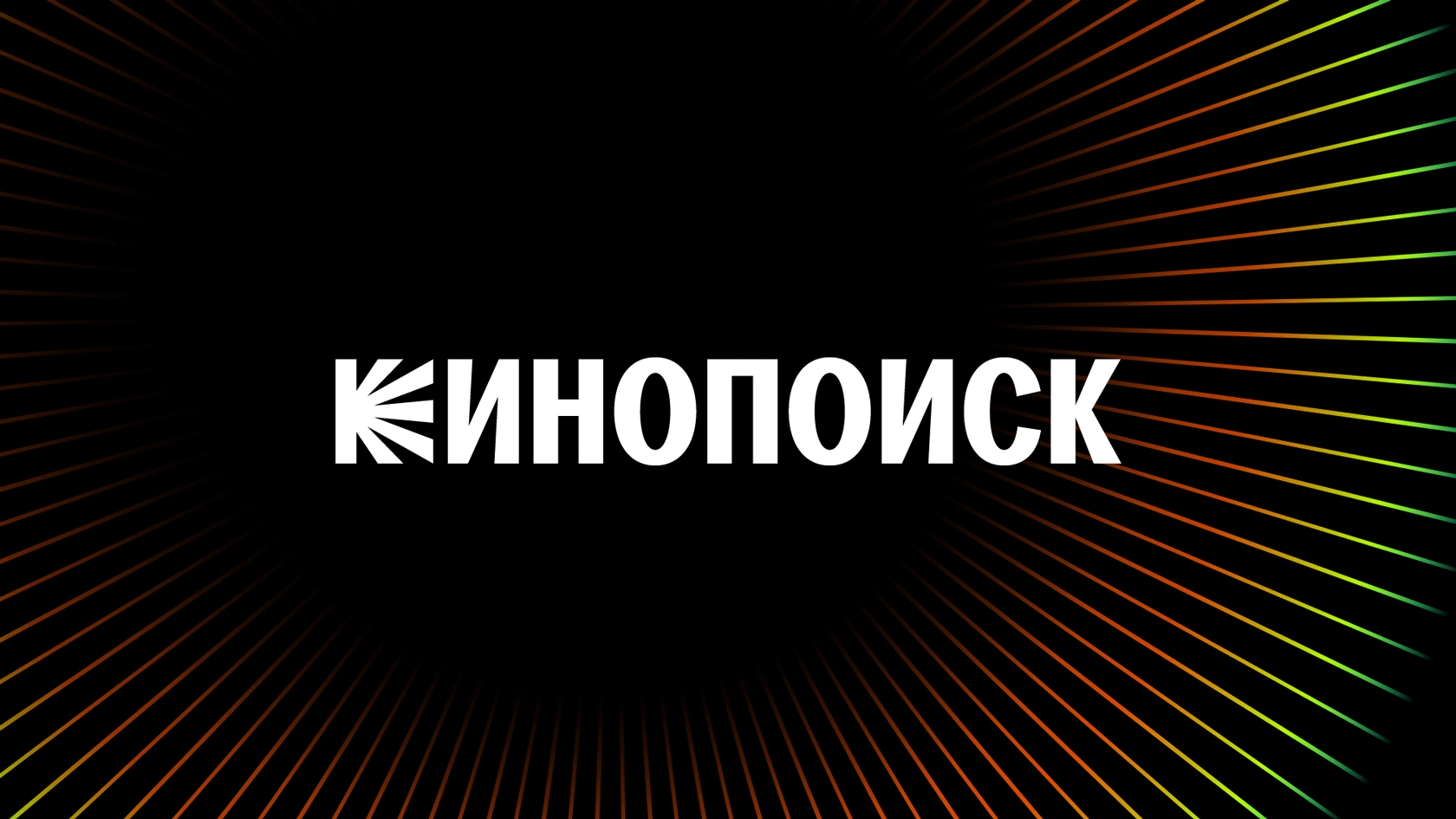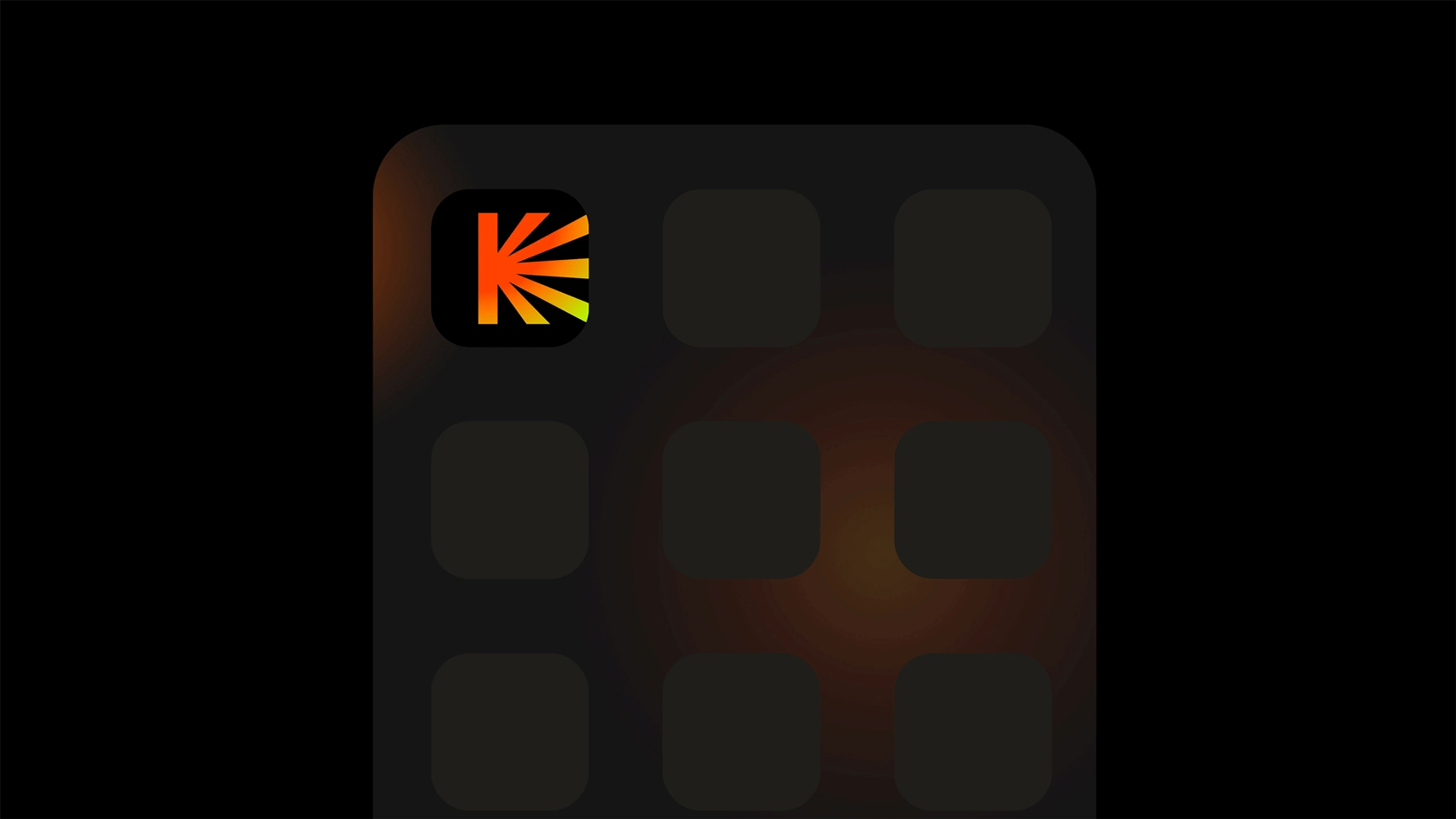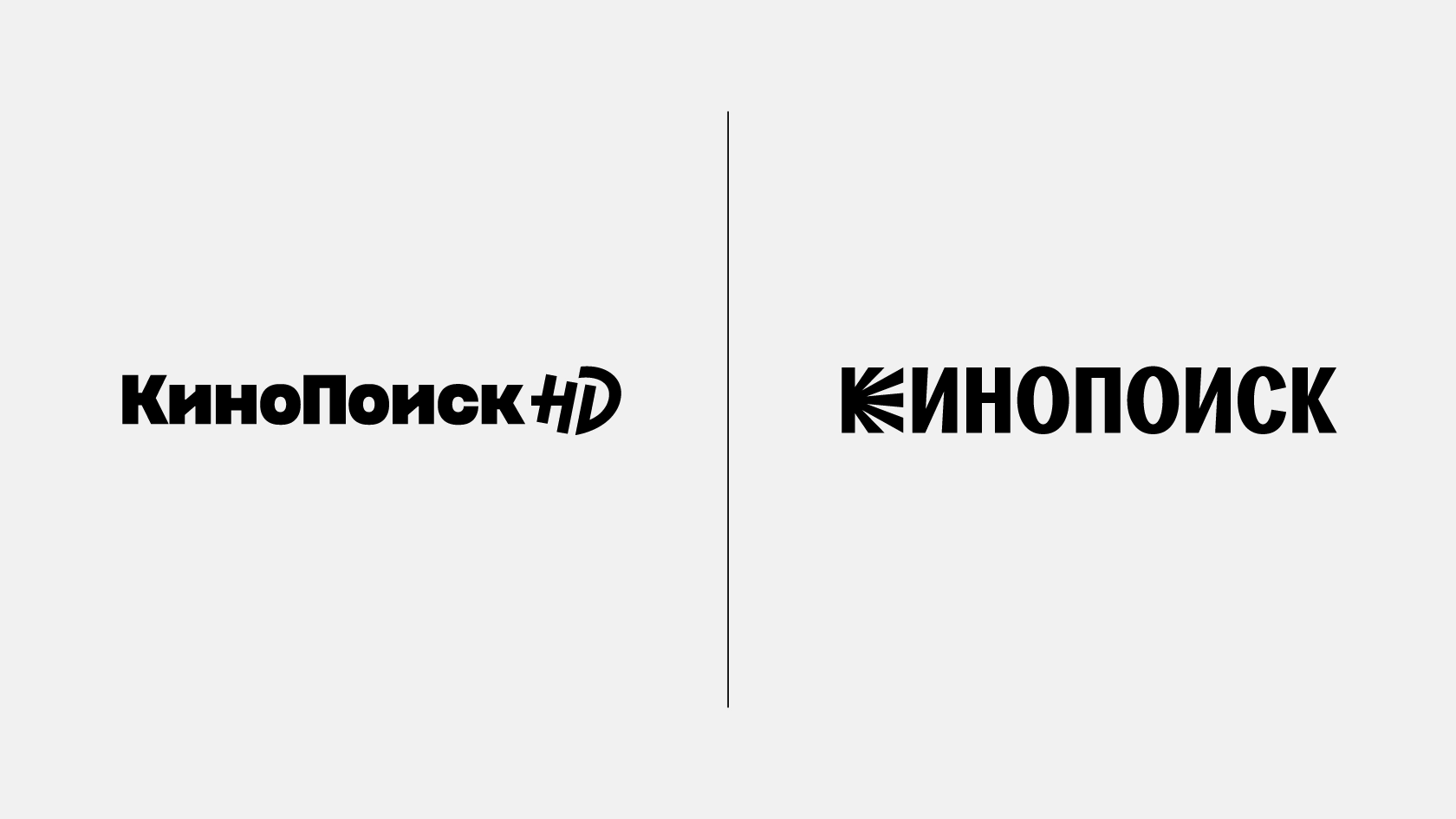
Новый логотип Кинопоиска—кросс-платформенный, притягивающий, адаптируемый
В честь своего совершеннолетия Кинопоиск обновился: изменились не только стиль и бренд-стратегия, но и визуальный контент. А КоФо позвали создавать логотип и знак платформы.
Новый знак—«жуквица»—отражает главную идею—объединение людей вокруг сервиса. Она присутствует в коммуникациях, иконках, встроена в текст, адаптируется под шрифты, меняет насыщенность и контраст. Знак такой же живой и энергичный, как новый Кинопоиск.
И не только «жуквица» уникальна: в других формах логотипа также видны лучи. Это помогло нам связать знак и лого. Проектируя логотип, мы учитывали всю обновленную систему сервиса, его интеграцию на сайт, пропорции букв, насыщенность для мелких размеров и работу в формате TV-приложений. Наша буква
К так узнаваема, что она обязательно притянет ваш взгляд среди других сервисов.
До | После